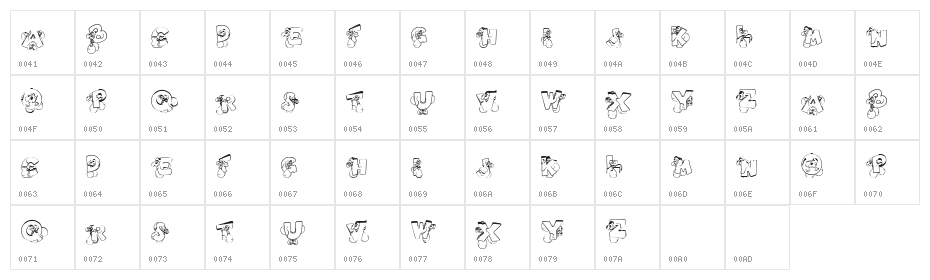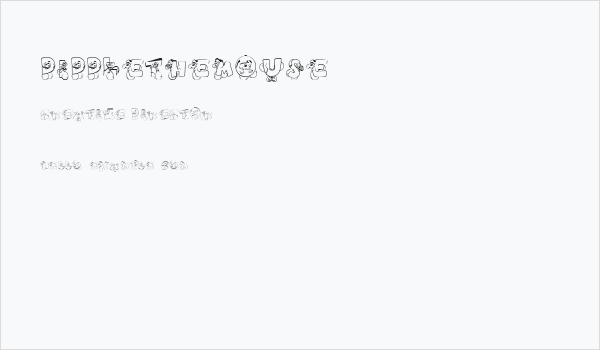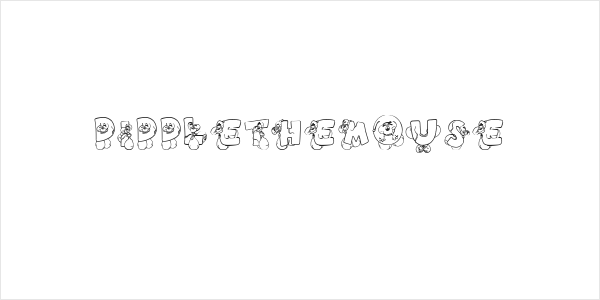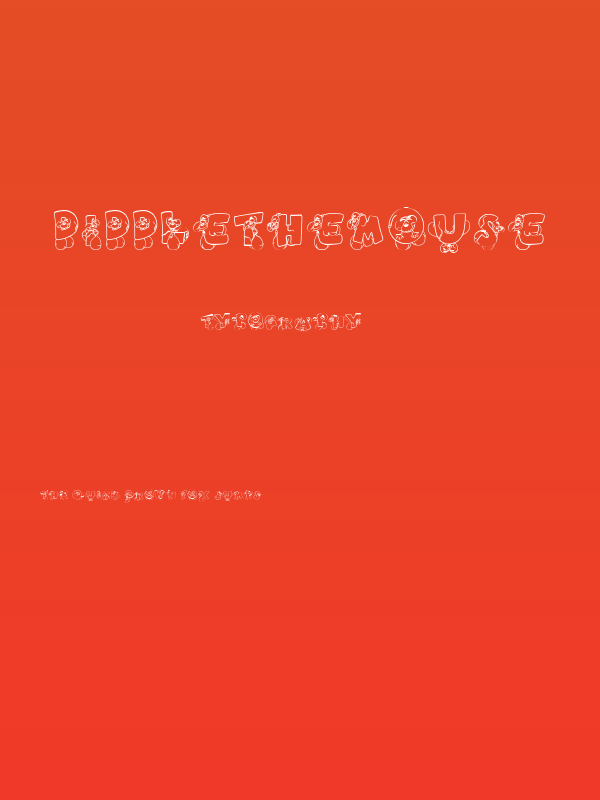
DiddleTheMouse Font
DIDDLETHEMOUSE Groß
DIDDLETHEMOUSE Kleinbuchstaben
DIDDLETHEMOUSE Anderer Schreiben
| Gesamtstil | Playful, Whimsical |
| Vorgeschlagene Projekte | Ideal for children's books, playful branding, party invitations, and any project needing a fun and lively touch. |